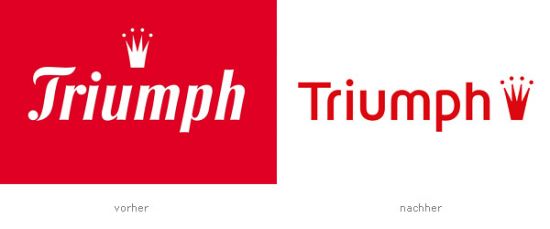
Triumph – Neues Logo
Der internationale Hersteller von Dessous und Unterbekleidung wird ab Juni 2007 mit einem neuen Logo und ab 2008 weltweit mit neuem Corporate Design auftreten. Das neue Logo sei Ausdruck eines umfassenden Prozesses mit dem Ziel, die Wahrnehmung der Marke Triumph global zu harmonisieren. Ein Schritt in diese Richtung sei die Definition einer dreiteiligen Markenarchitektur. So ruht der Brand nun auf den drei Säulen “Miss Triumph”, “Triumph” und “Classics by Triumph”. In der Kommunikation sollen diese Säulen durch jeweils eigenständige visuelle Welten umgesetzt werden (Quelle: persoenlich.com). Entwickelt wurde das neue Logo und das zukünftige Corporate Design von MetaDesign.
ähm ... habt ihr ’ne meinung dazu?
ich glaube die spinnen die römer.
Mir fällt dazu gar nichts ein, das ist einfach nur strunzlangweilig und gequält modern. Warum machen Firmen sowas? Zumal wenn sie schon eine gestandene Marke haben? Aber da hat ihnen wahrscheinlich einer die Ohren vollgequatscht mit "dem Brand" usw. Anzugträger, pfft ...
Das alte Logo ist meiner Meinung nach elegant, classy, in einem positiven Sinn altmodisch; das hätte man doch – wenn überhaupt! – sanfter ›renovieren‹ können. Für mich nicht nachvollziehbar ist zudem, dass die Krone nun abgegeben – bzw. abgelegt wurde. Auch die Schrift wäre nicht meine Wahl gewesen.
sowas können sich nur kranke marketing- und werber-fuzzis einfallen lassen.
eine marke die emtionen und klasse transportiert hat einfach zu zerstören ...
schlimm.
florian hat recht. dieses »wir haben die krone abgenommen und niedergelegt«
ist ziemlich schade. ist der chef gestorben? der könig abgetreten?
damit verliert das logo seine dekadenz
Mir fällt dazu gar nichts ein, das ist einfach nur strunzlangweilig und gequält modern. Warum machen Firmen sowas? Zumal wenn sie schon eine gestandene Marke haben? Aber da hat ihnen wahrscheinlich einer die Ohren vollgequatscht mit "dem Brand" usw. Anzugträger, pfft ...
Exakt, alles kaputtmachen versuchen, was man vorher eigentlich hatte …
Vielleicht sollte man das Image der bisherigen Brand intelligent zu verstärken suchen und nicht sowas – "einfach aufgeben", urgx.
triumph war mir sympathisch, seit ich mal die unternehmensgeschichte gelesen habe. schon vor 50 jahren verkauften die hässliche damenunterwäsche, nun ist sie halt stylisch und das logo passte genau deswegen ganz gut. und nun das.. wuäh.
Kronen hab ich auch.
Aber schaut Euch mal das "alte" (?) Logo ganz unten an. DAS nenn ich modern.
Das hieß doch früher "Triumph -krönt die Figur".
das sitzt bei mir so fest im akustischen Gedächtnis wie
So eine Marke zerbröselt man doch nicht mutwillig.....
Hey, romibello, rock Dich mal bei Triumphens rein! Wenn die Dein Logo sehen, merken sie vielleicht noch was.
Deren neues Logo? Völlig daneben. Total lustloslangweiliger Quatsch.
die ausführung des neuen logos mag kritikwürdig sein, aber: ich glaube, das »problem« von triumph – falls sie überhaupt eines haben – liegt darin, dass die marke und das logo nicht in einem positiven sinne altmodisch wirken, sondern piefig und bieder. die ware ist es meiner meinung nach nicht, aber die jungen frauen, die ich kenne, kaufen, wenn sie sich gute teure unterwäsche gönnen wollen, meist etwas anderes als triumph. vielleicht will man das ändern. nicht umsonst gibt es bereits andere markennamen wie sloggi, unter denen das unternehmen unterwäsche verkauft. da hilft ein altes logo wenig, das ein paar männliche grafiker »classy« finden. oma, die einmal im jahr ein hautfarbenes modell kauft, um ihre welken euter zu stützen, bleibt der marke sowieso treu. ob es das neue logo für den laien reißt? ich werd mal ein paar potenzielle kundinnen in meinem bekanntenkreis unrepräsentativ befragen.
Also erstmal mal macht ein Logo allein keine Marke.
Da spielen alle Kommunikationsmittel und -elemente zusammen,
Farbklima, sonstige grafische Elemente etc. Wenn man das alles sehen würde, könnte man sagen, ob das langweilig etc. ist,
Zum zweiten kann ich noch etwas aus erster Hand dazusagen, meine Teamkollegen haben nämlich an dem Pitch der dafür ausgeschrieben wurde mitgemacht (und verloren).
Die haben tatsächlich ein Image-problem, sie wollten modern sein, aber in D kaufen nur Omis und altmodische Leute Triumph.
Übrigens gilt Triumph im Asien z.B. als superchic.
Die entscheider sind übrigens nur Männer die wissen ganz bestimmt, was Frauen wollen... :)
Das alte Logo hatte seinen Charm, aber es ist halt altmodisch,
bzw. unterstreicht es.
Ich persönlich finde das neue auch nicht überrragend, ein bißchen ängstlich vieleicht, aber es ist auf jeden Fall weniger altbacken wie vorher.
Was meint ihr, warum machen eignentlich immer alle Agenturen, wenn sie ein "modernes" Redesign machen erstmal was mit einer Grotesken?
Als ob das allein schon midern macht...
Ein international konsistentes und kohärentes Markenbild und eine Verjüngung der Marke ist das Ziel der Brandingspezialisten
...und da sind wir wieder beim Thema Globalisierung. Ein Logo einer Firma dieser Größenordnung muss heute global funktionieren. So schade ich es finde, dass sie fallengelassen wurde, aber wer weiß, ob die Krone nicht an anderen Plätzen dieser Erde vielleicht negativ belegt ist und dort zum Beispiel mit der Kolonialzeit in Verbindung gebracht wird? Das ist jetzt rein hypothetisch. Man müsste mehr über die Hintergründe erfahren...